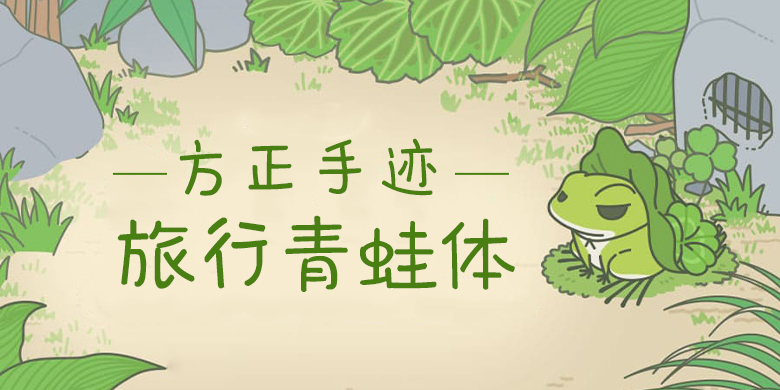
方正手迹-旅行青蛙体 品牌: 方正手迹
设计师: 俞亦婷
创意\卡通\可爱\有趣\广告\影视\电商\海报\包装\新媒体\综艺\游戏\动漫\标题\杂志\书籍\创意\书写 旅行青蛙体,简洁的笔画,轻松大方的字形,温婉迷人,少女气息满满。适用于青少年儿童类、文艺类书刊、漫画综艺字幕、品牌广告和产品包装设计,以及社交网络的个性化用字。